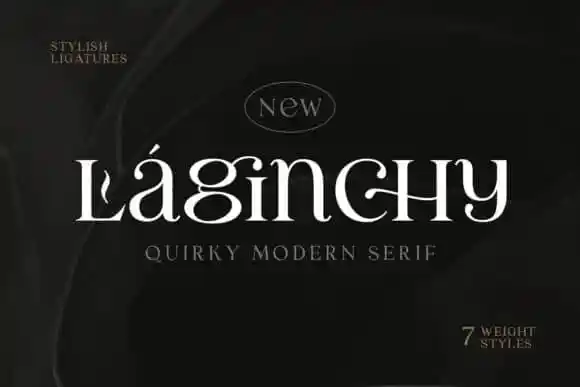
Laginchy Serif Font – Fonte Grátis
Laginchy Serif Font
Laginchy Serif é uma fonte serif que transmite elegância e alegria com sua delicada curvatura. Idealmente projetada para saridezra por meio de 99designs, essa fonte não apenas apresenta uma aparência única e intrigante, mas também se destaca pela versatilidade no design. Seja para criar cartões de casamento ou arte de embalagem de notas, postagens nas redes sociais ou qualquer outra criação que necessite do seu charme, Laginchy Serif oferece um estilo impressionante e único. Fique encantado por sua capacidade versátil e se inspire em suas possibilidades criativas, elevarão seu trabalho a outro nível.